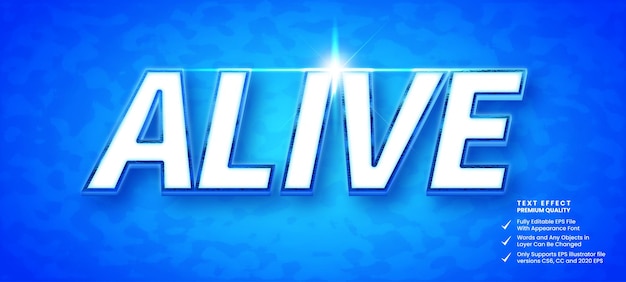
Redigerbar textstileffekt – textstiltema: Modern redigerbar texteffekt, livfull modern färg, skinande. Textstileffekt, redigerbara typsnitt, vektorfiler